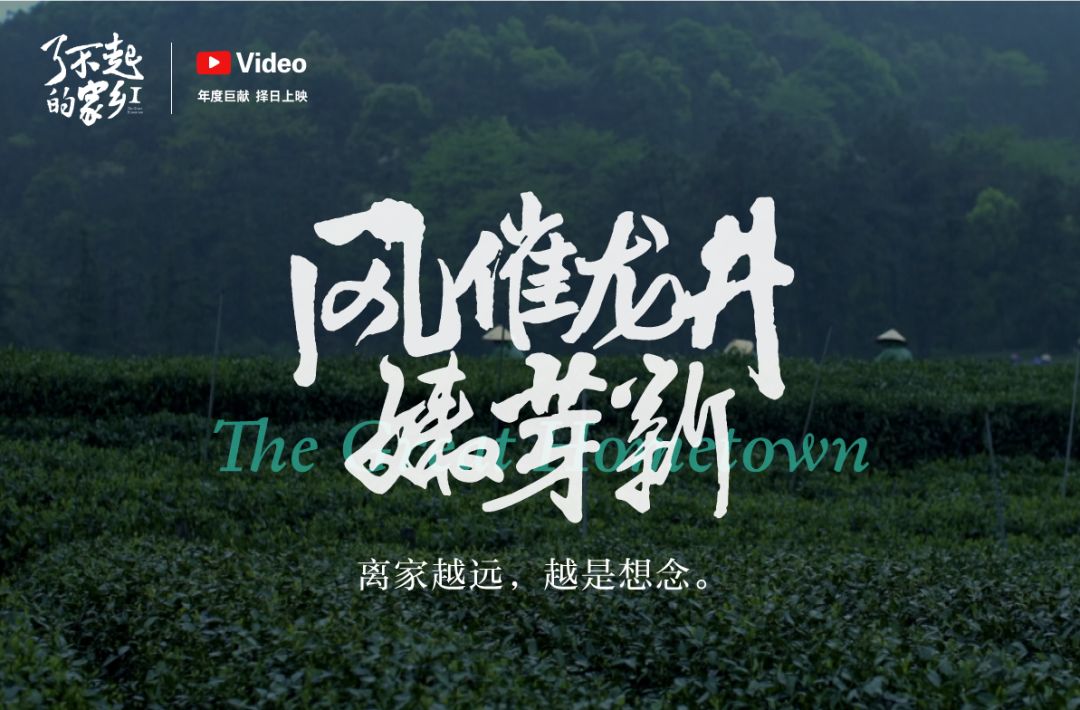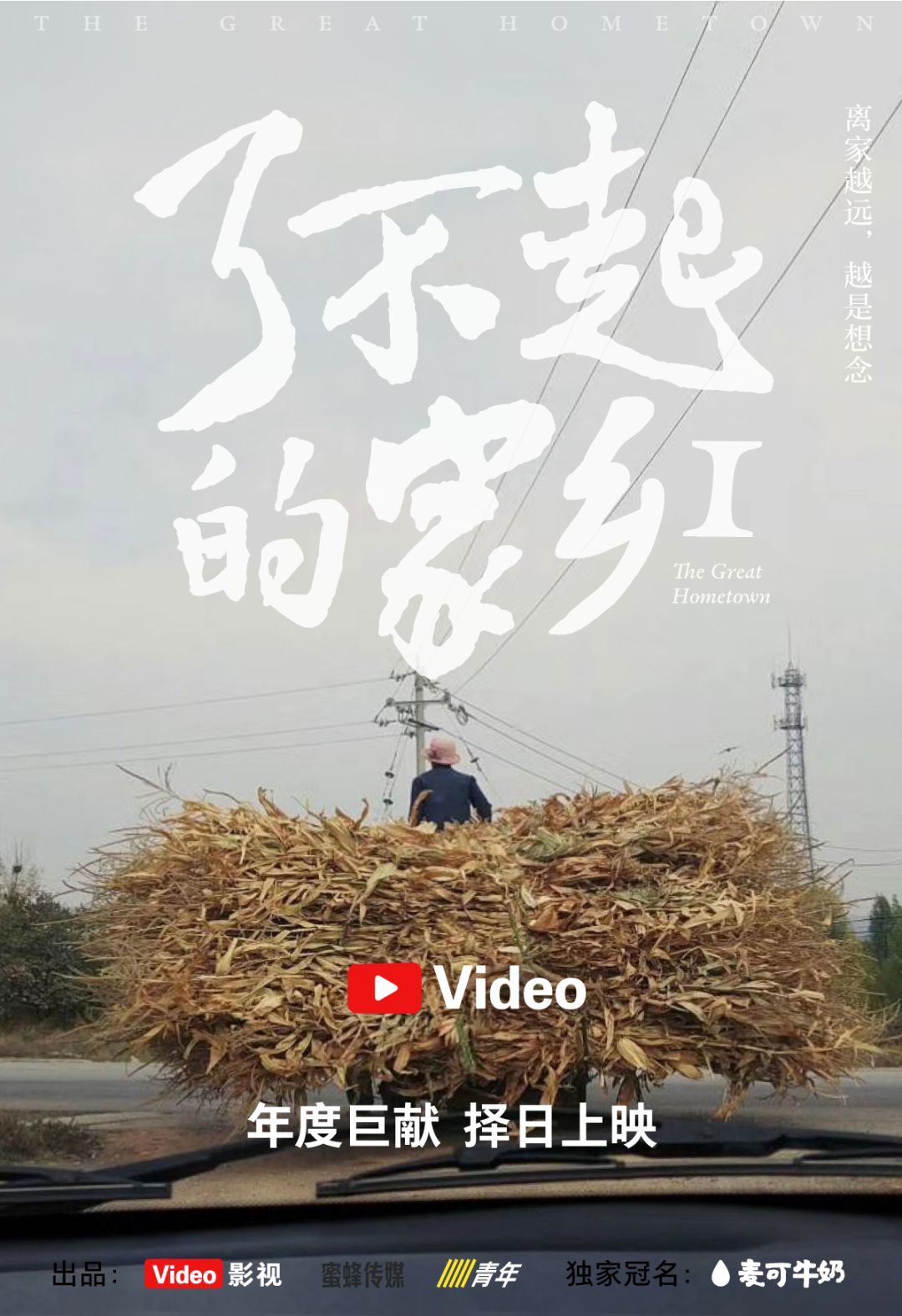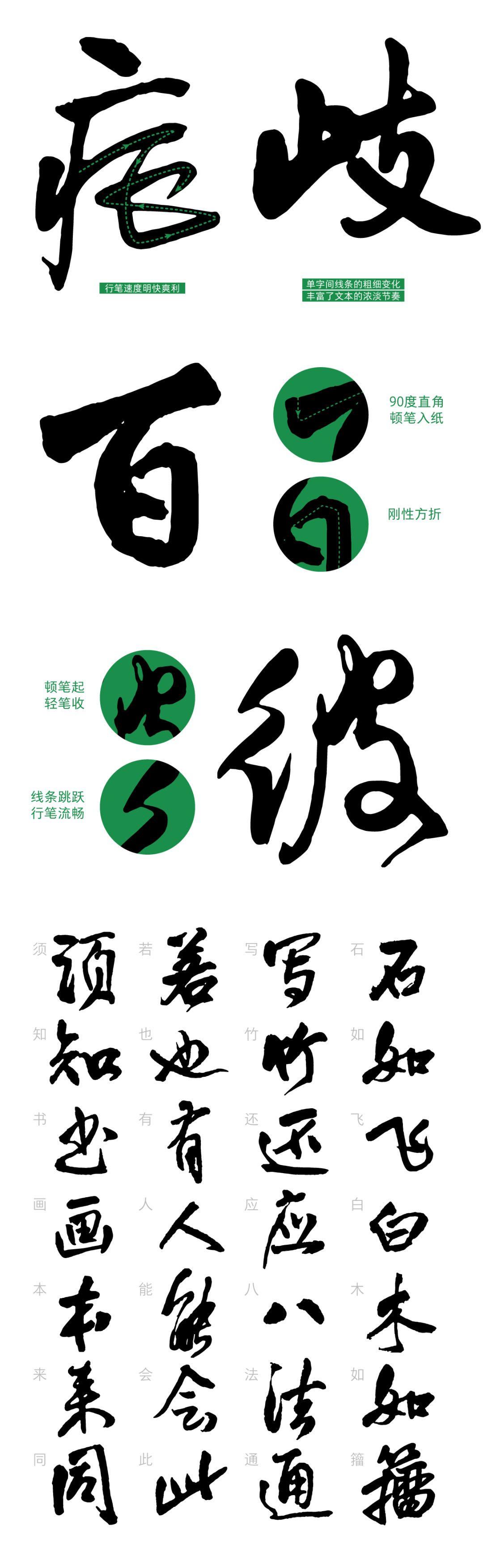
方正王铎行草
字体品牌: 方正字库 中华精品字库 整理/设计:禚效锋,杨龙龙 字体分类:行书、草书 字体属性:精品字 字符集:简繁扩展(GBK)、大陆简体(GB2312-80) 发布时间: 2019
王铎(1592-1652),清书法家。字觉斯,号嵩樵,河南孟津人。工行草书,深入阁帖,又得力于颜真卿、米芾二家及历代草法。拓古法而大之,笔力雄健,长于布白,揭开大字行草书的新篇。兼能山水、兰竹。传世墨迹甚多,有《拟山园帖》集刻其法书。
字体特征:以王铎主要传世墨迹为开发依据。运笔酣畅,劲健洒脱,变化多端,仪态万方。
审稿专家:徐海、林景辉
王铎(1592-1652),清书法家。字觉斯,号嵩樵,河南孟津人。工行草书,深入阁帖,又得力于颜真卿、米芾二家及历代草法。拓古法而大之,笔力雄健,长于布白,揭开大字行草书我的新篇。兼能山水、兰竹。传世墨迹甚多,有《拟山园帖》集刻其法书。
方正王铎行草以王铎主要传世墨迹为开发依据。运笔酣畅,劲健洒脱,变化多端,仪态万方。
作为“中华精品字库工程”的重要组成部分,方正王铎行草的开发,经历了收集字稿、字稿扫描、字形选择、精细设计、补字创写、字形检查、专家审核、封装成库共8个步骤。王铎行草的最终呈现,是字体设计师和书协专家们精诚合作、一同挑战困难、追求极致的成果。方正王铎行草——设计团队:禚效锋、杨龙龙、杨盈盈、王文娜、张蕾、张璋、刘会会、陈昕。审稿专家:徐海、林景辉。
作为一款经典复刻字体,方正王铎行草在满足电脑字库规范性的同时,生动再现了书法名家的个性特征、保留了书法字的灵动性。其苍劲跳跃、雄健恣意、洒脱豪放的个性特征,在当下审美语境下,仍彰显着潮流气质。无论是包装、广告,亦或影视综艺、游戏动漫,它的应用都会有很强的视觉感染力。希望它的广泛应用,能唤起大家血液里对中华书法文化的情感。- 方正王铎行楷模拟应用效果 -